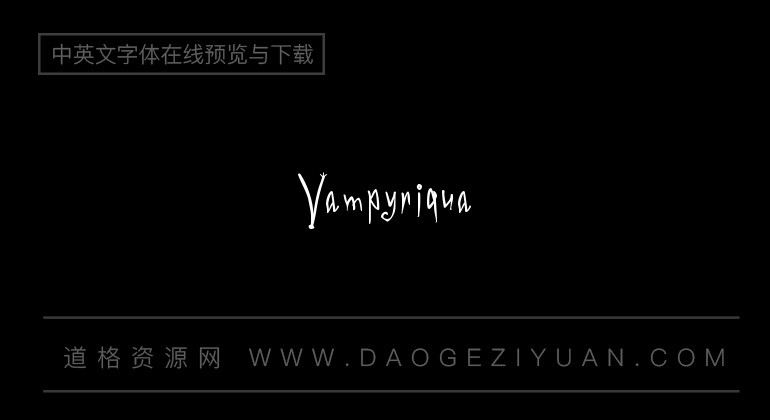
Vampyriqua
Vampyriqua 是一款有趣的字体,它由芬兰设计师 Tuomas Nikkinen 创作。它是一种混合字体,将西方文字的精细笔画与日本漫画的粗犷风格相结合,形成一种独特的外观。Vampyriqua 字体的特点是它的折衷风格,拥有精致的笔画和活泼的色彩。它具有趣味性,可以用于卡通、漫画、海报等。
Vampyriqua是一款非常不错的手写艺术字体,具有很好的视觉感,适合于文化类的宣传设计、商业类品牌的广告和产品包装设计以及个性化文字排版等较多场景。